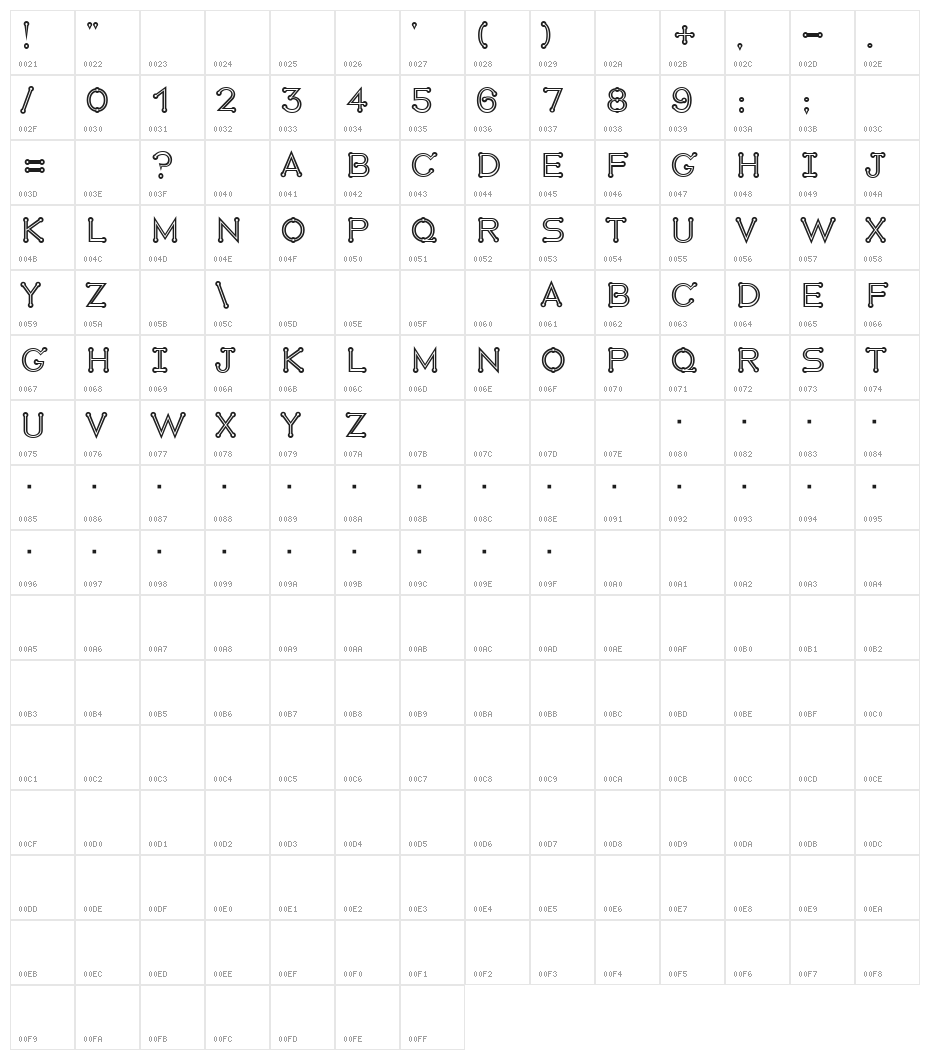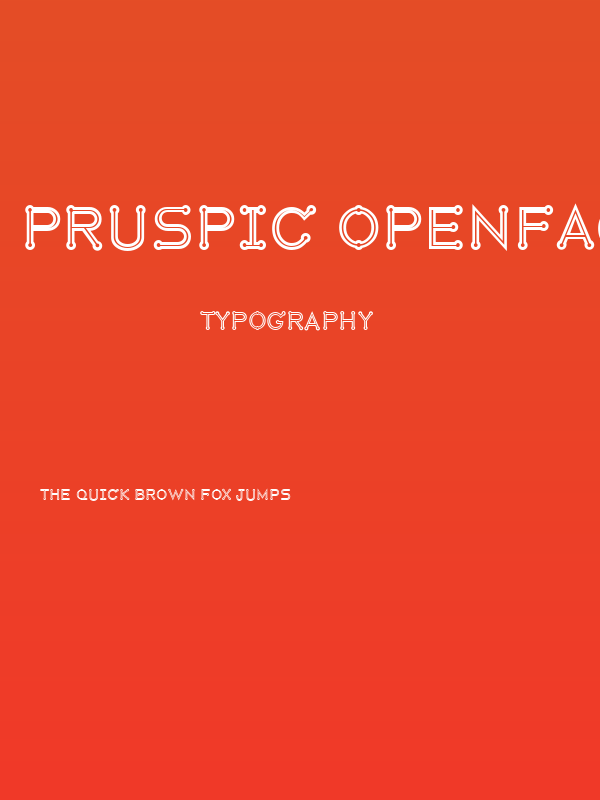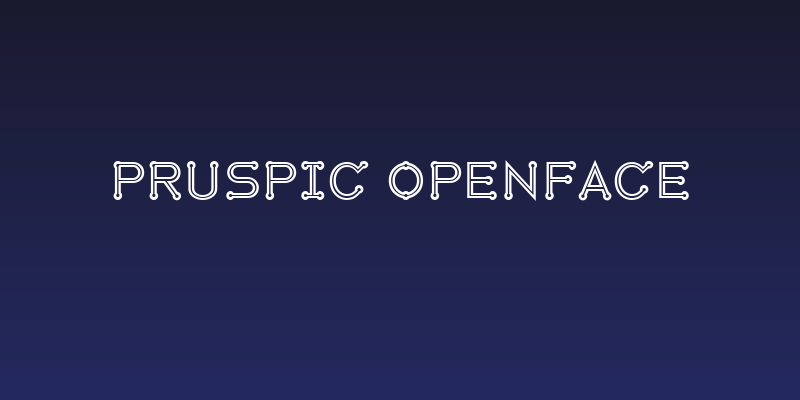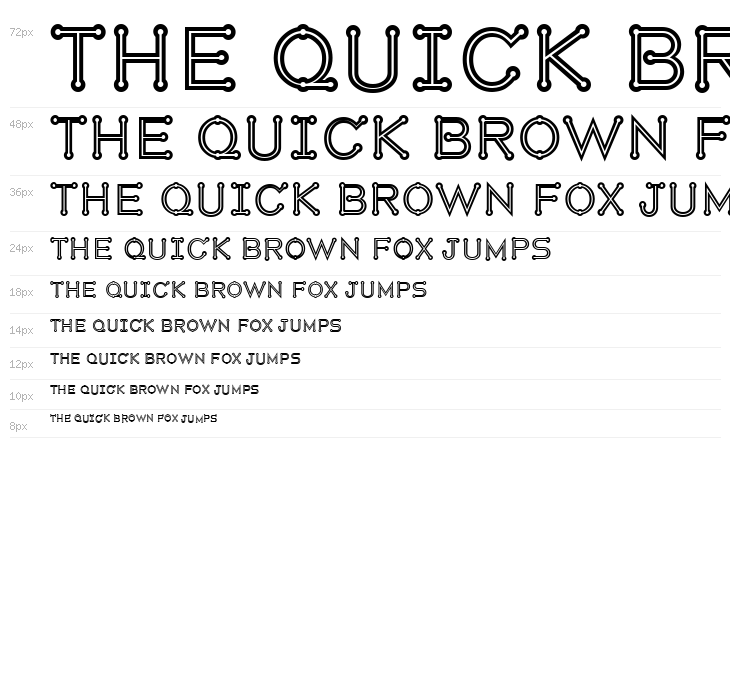
Pruspic Openface Font
| النمط العام | Modern, Decorative |
| حالة الاستخدام | Logos, Posters, Creative Branding |
| مشاريع مقترحة | Ideal for creative projects such as posters, logos, and branding materials where a unique and artistic font is desired. |